モリサワ2023年新書体としてA1明朝の新ウエイトを発表!10月18日(水)11時より提供開始
モリサワは、2023年10月18日(水)11時より、Morisawa FontsおよびMORISAWA PASSPORTアップグレード2023年10月版として2023年新書体の提供を開始することを発表した。
アップグレード2023年10月版では、合計23ファミリー85書体が登場。
7月12日付に発表された内容に加えて、ファミリー化してリニューアルした「A1明朝(AP版)」や、「UD新ゴ コンデンス(AP版)」、「ヒラギノ丸ゴ」のW7をリリースする。
「A1明朝」は、写真植字機用書体に由来を持つオールドスタイルの明朝体で、先端や交差部分に角の丸みが施された「墨だまり」の味わいを特徴としている。
2005年のデジタルフォント化以来、多くの媒体で活用されている、モリサワを代表する書体の1つとなる。
長らく単一ウエイトで提供してきたが、今回のAP版としてのリリースにあたり、従来の太さを「R」とし、新たに「M」と「B」を追加した。
さらに欧文も、16世紀のフランスにルーツをもつローマン体に着想を得たクラシカルなデザインにリニューアルした。
また、「UD新ゴ コンデンス(AP版)」はAP化に加え、欧文は「Clarimo UD PE Condensed」をベースに、和文と調和するよう調整し、より高品質な混植が可能になった。
そして今シーズンのリリースによって、2023年現在のモリサワライブラリーにおけるA-OTF書体はAP版書体化、A-OTFかな書体は全て総合書体化され、AP版書体は和文・欧文ペアカーニングと最新のIVSに対応しており、より美しい組版を実現できるようになった。
これらのほか、株式会社SCREENグラフィックソリューションズのヒラギノフォントのラインナップとして、基本書体である「ヒラギノ丸ゴ」にW7のウエイトを追加される。
2023年新書体の特設ページを9月13日(水)から公開した。
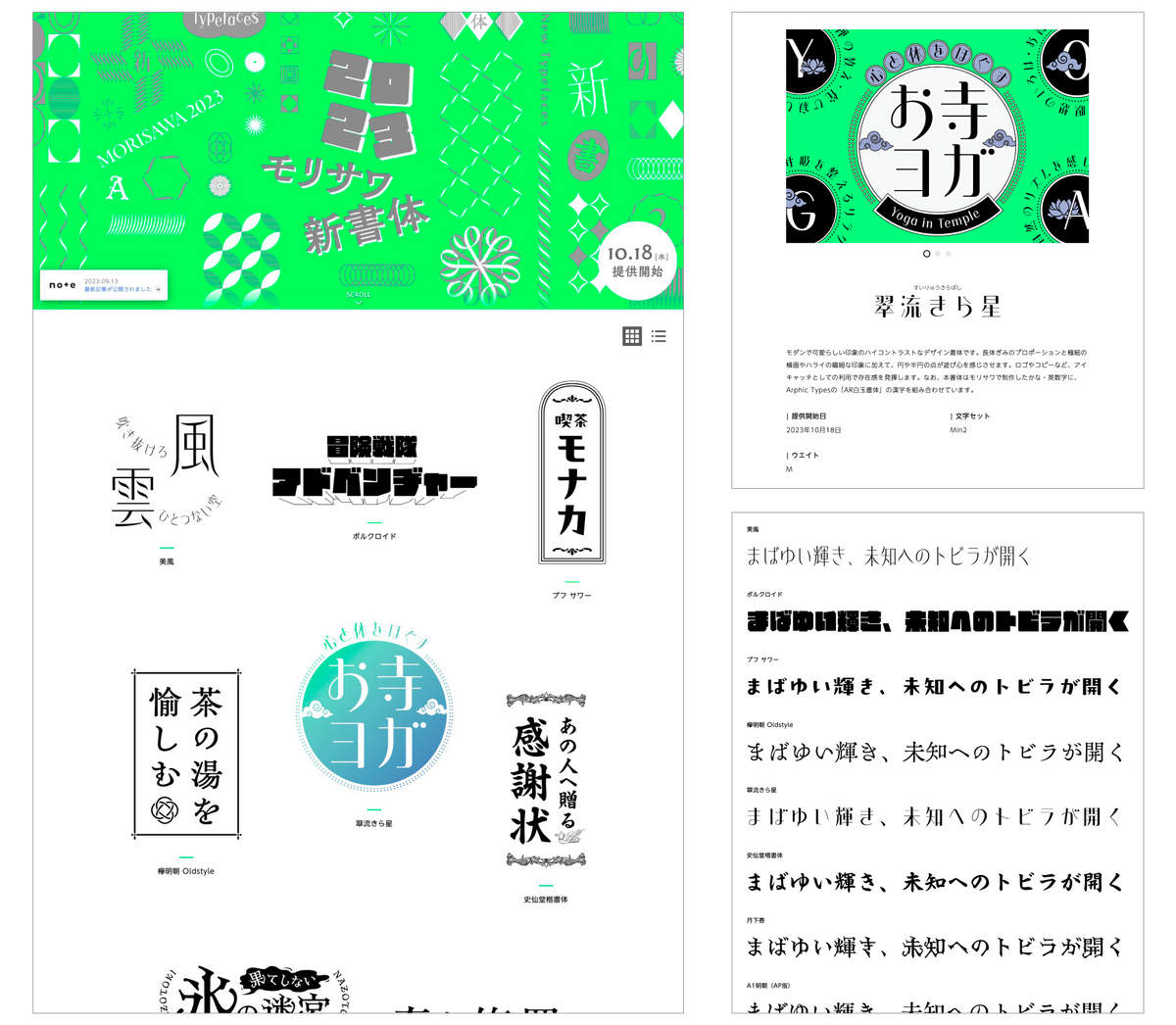
新書体の個性を表現したロゴデザインをあしらい、10月のリリースがさらに楽しみになる各書体情報を紹介している。